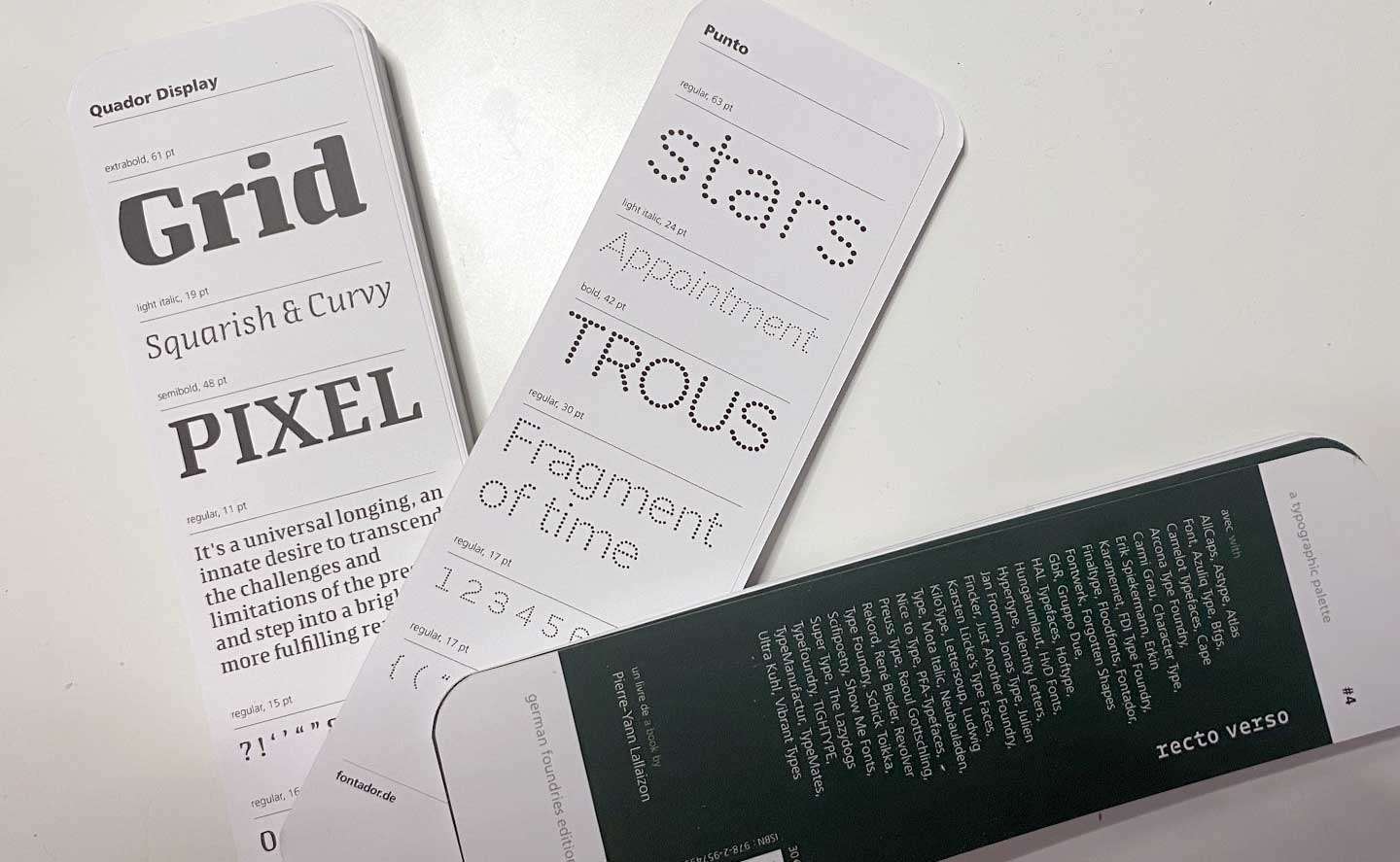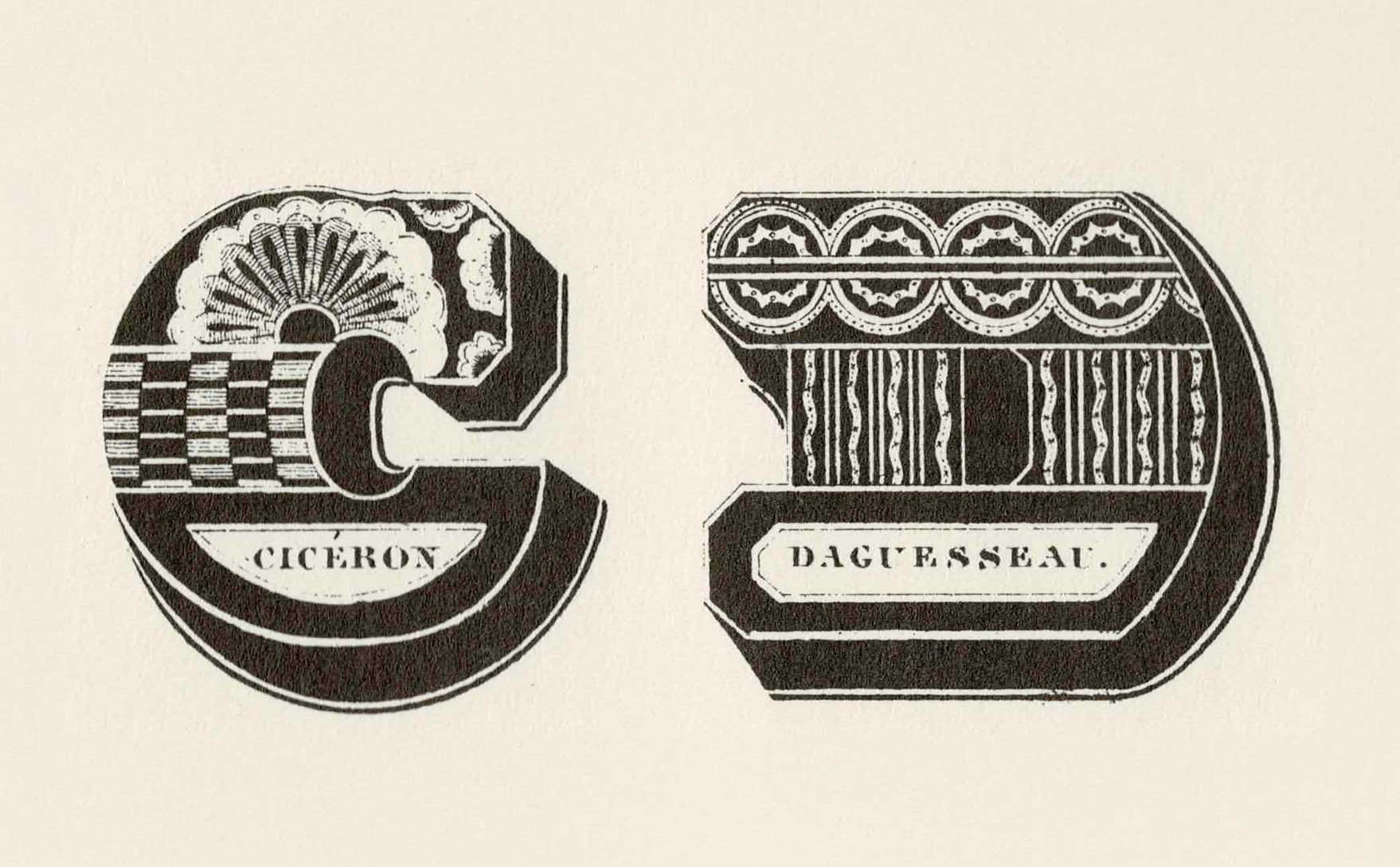
Cubo – from typeface to applied graphics
Jean Midolle: Alphabet Lapidaire Monstre, aus Spécimen des écritures modernes, Émile Simon fils, Strasbourg, 1835. Gemeinfrei.
Does Surrealism have a Typographic Language?
I have been reflecting on the connection between typographic styles and broader movements in art and architecture.
For many historical periods, there seems to be a fairly clear typographic counterpart: for example, Renaissance and humanist typefaces, Modernism and geometric sans-serif typefaces, and so on …
But what about Surrealism?
Are there any typefaces, type styles or typographic movements that could seriously be described as ‘surrealist’? If so, what characteristics would distinguish them? Are there historical examples from the Surrealist period itself, or later typeface designs that embody Surrealist ideas typographically?
Or does Surrealism differ fundamentally from movements such as Art Nouveau, Art Deco or the Bauhaus, in that it manifests itself primarily through visual language, composition, collage and visual context, rather than through the design of the letterforms themselves?
Is Surrealism a missing category in typographic classification, or simply a movement that never developed its own recognizable typographic language?
»Curve Display: Eine Schrift für besondere Anlässe«
Fontador: Curve Display is "Steven Hellers Font of the Month"
Release: Talaris - A softly blurred sans
Talaris zeigt sich als weichgezeichnete, leicht überblendete Grotesk mit fließenden Übergängen und bewusst entschärften Konturen. Formal erinnert die Schrift an die experimentelle Digitalkultur der 1990er Jahre und steht in deutlicher Nähe zu Emigre- und Fuse-Fonts, bei denen Imperfektion als gestalterische Haltung verstanden wurde. Im Unterschied zu ihren historischen Vorbildern wirkt Talaris jedoch kontrollierter und systematischer, mit klarer typografischer Logik.
Die Schrift bietet mit 12 Schnitten und der Unterstützung von 144 Sprachen eine große Flexibilität für alle typografischen Anforderungen.
Talaris verbindet den Geist der digitalen Avantgarde der 90er mit zeitgemäßer Anwendbarkeit in Editorial-, Branding- und Konzeptdesign.
Release: Talaris - a softly blurred sans
Talaris presents itself as a softly blurred, subtly overlaid grotesque with flowing transitions and deliberately softened contours.
Formally, the typeface recalls the experimental digital culture of the 1990s and stands in clear proximity to Emigre and Fuse fonts, where imperfection was embraced as a deliberate design attitude.
In contrast to its historical predecessors, Talaris appears more controlled and systematic, guided by a clear typographic logic.
With 12 styles and support for 144 languages, the typeface offers a high degree of flexibility for a wide range of typographic applications.
Talaris bridges the spirit of the digital avant-garde of the 1990s with contemporary usability in editorial, branding, and conceptual design.
German foundries edition of recto verso.
Quador Display and Punto in the german foundries edition of recto verso.
Release: Curve Display - An experimental Didone
Curve Display ist die mystische Schwester von Curve. Sie ist eine zeitgenössische Display-Schrift, die den eleganten Klassizismus der Didone-Tradition mit experimenteller Dekonstruktion verbindet. Sie hat eine große x-Höhe, superelliptische Formen, die bewusst gebrochen, fragmentiert oder gespiegelt sind. Das Ergebnis ist ein charakterstarkes Spannungsfeld zwischen Eleganz, Irritation und zeitgenössischem Ausdruck. – Curve Display steht für starke visuelle Statements, die bewusst mit Lesbarkeit und Wahrnehmung experimentieren.
Curve Display is the related variant of Curve. It is a contemporary display font that combines the elegant classicism of the Didone tradition with experimental deconstruction. It has a large x-height and super-elliptical shapes that are deliberately broken, fragmented or mirrored. The result is a powerful tension between elegance, irritation and contemporary expression.
Curve Display stands for strong visual statements that deliberately experiment with legibility and perception.
Release: Enorm - a fluid sans
Enorm ist eine moderne, futuristisch angelegte Neo-Grotesk, die Klarheit und Zeitlosigkeit mit aktuellen und zukünftigen Technologien verbindet. Sie ist als typografisches Fundament für eine prägnante Markenkommunikation konzipiert.
Die große x-Höhe verbessert die Lesbarkeit in kleinen Schriftgraden und verleiht der Schrift zugleich einen offenen, großzügigen Charakter – sowohl in Print- als auch in digitalen Anwendungen. Umfangreiche OpenType-Features wie Ligaturen, kontextabhängige Alternativen und Stylistic-Sets sind in allen Schnitten integriert. Mit breiter Sprachunterstützung bietet Enorm hohe Flexibilität für vielfältige typografische Anforderungen.
Herbert Bayer beginnt Schriftraster aus geometrischen Grundformen zu entwickeln. Auch für ihn bleibt Schriftgestaltung eher eine geometrisch-formale Lösung, als die der Lesbarkeit. Seine zwei Jahre später entstandene »bayer universal« war charakteristisch und lesbar in größeren Schriftgraden, aber schwer erfassbar im Mengensatz.
Bayer übernimmt den »vorkurs schrift« und orientiert sich weiterhin am geometrischen Raster.